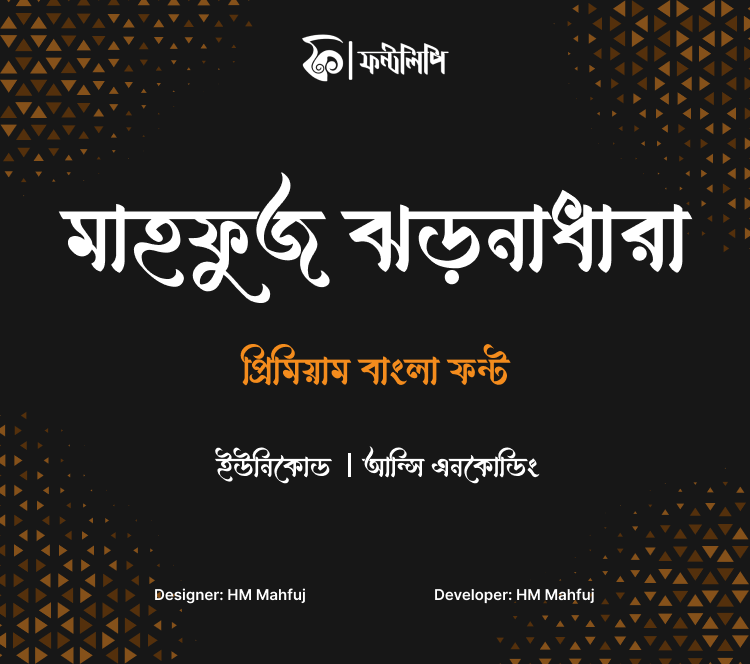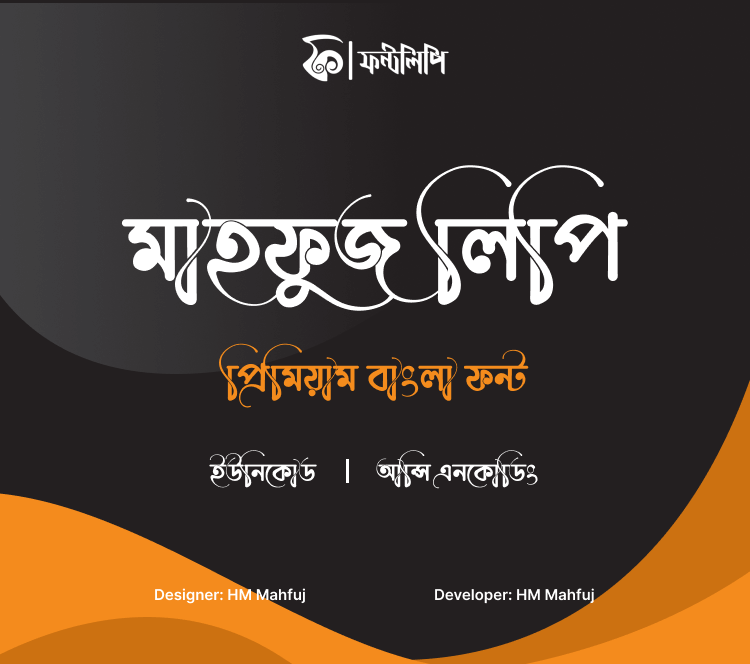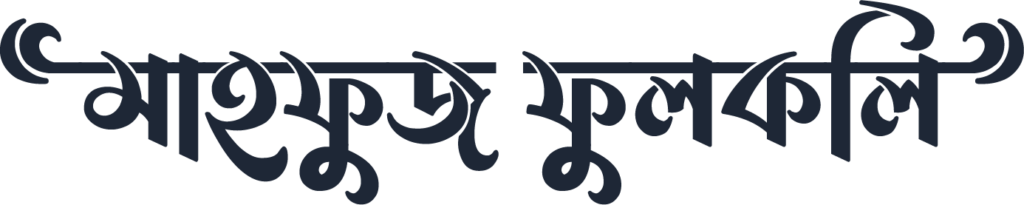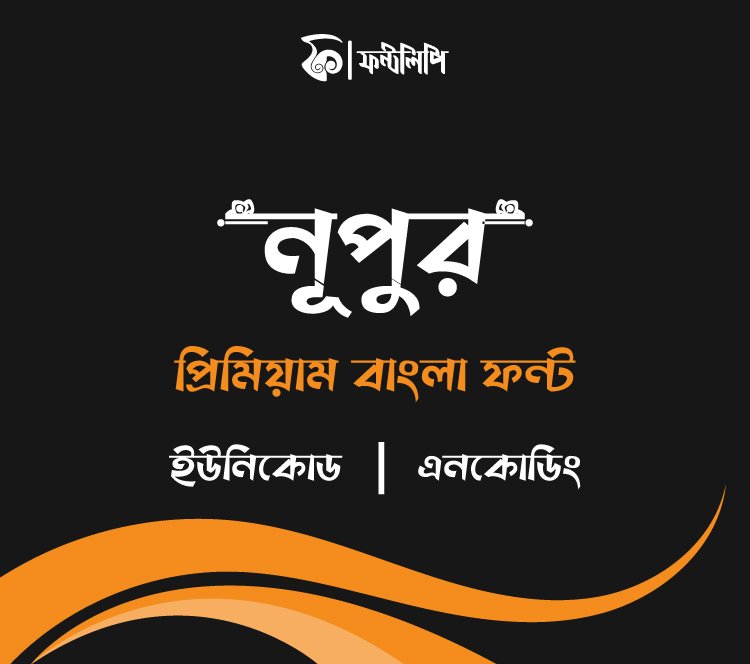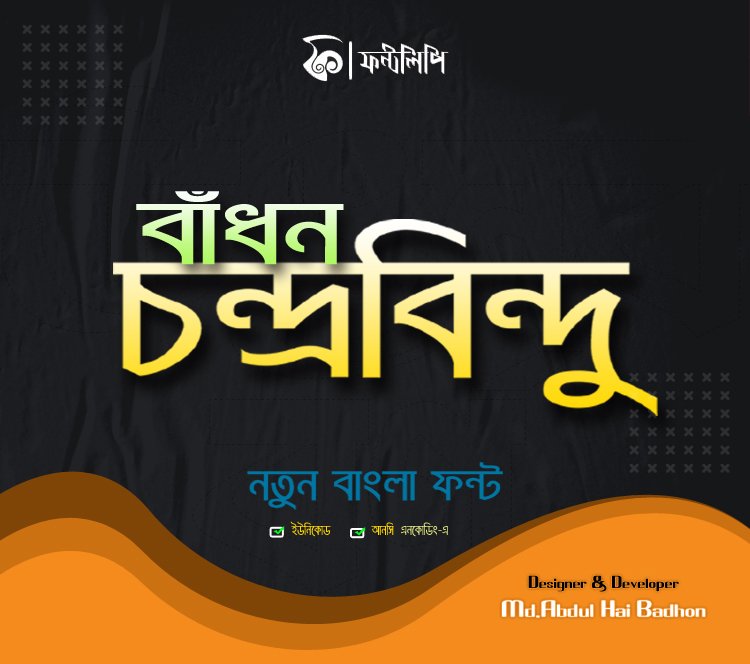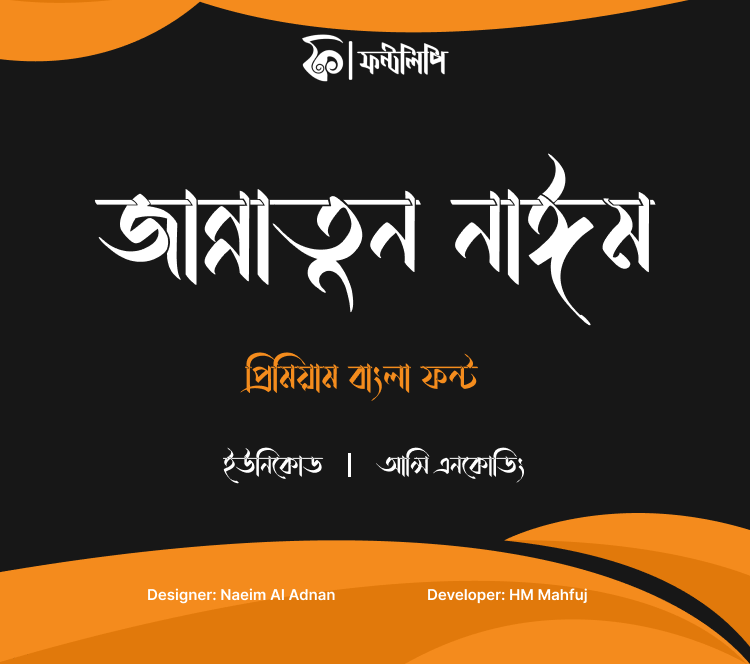
বাংলা পোস্টার ডিজাইনের জন্য সেরা ১০টি বাংলা ফন্ট: রিভিউ ও বিশ্লেষণ
বাংলা পোস্টার ডিজাইন এখন আগের চেয়ে আরও বেশি জনপ্রিয়। ডিজিটাল মার্কেটিং, সোশ্যাল মিডিয়া, অফিসিয়াল বিজ্ঞাপন, শিক্ষা প্রতিষ্ঠান—সবখানে পোস্টারের চাহিদা বাড়ছে। সুন্দর ও মানানসই ফন্ট ব্যবহার করলে পোস্টার সহজেই মানুষের দৃষ্টি আকর্ষণ করে, পোস্টারের গুরুত্ব বাড়ে, এবং বার্তা পরিষ্কারভাবে পৌঁছায়। ডিজাইনারদের জন্য ফন্ট নির্বাচন সবচেয়ে গুরুত্বপূর্ণ বিষয়গুলোর একটি। বাজারে অনেক বাংলা ফন্ট আছে, কিন্তু সবগুলোই পোস্টার ডিজাইনের জন্য উপযুক্ত নয়। কিছু ফন্ট খুব সুন্দর হলেও পড়তে কষ্ট হয়, আবার কিছু ফন্ট দেখতে ক্লাসিক হলেও আধুনিক পোস্টারে মানানসই হয় না।
আজ আমরা এমন ১০টি বাংলা ফন্ট নিয়ে আলোচনা করব, যেগুলো পোস্টার ডিজাইনের জন্য দারুণ উপযোগী। ফন্টগুলো সরাসরি ফন্টলিপি ডটকম থেকে সংগ্রহ করা হয়েছে এবং প্রতিটির জন্য সংক্ষিপ্ত রিভিউ, মূল বৈশিষ্ট্য ও ব্যবহারিক উপকারিতা তুলে ধরা হয়েছে। এই বিশ্লেষণ শুধু ডিজাইনারদের জন্য নয়, যারা নতুন পোস্টার তৈরি করতে চান বা ফন্ট নিয়ে এক্সপেরিমেন্ট করতে চান, তাদের জন্যও সহায়ক।
পোস্টারের জন্য সঠিক ফন্ট নির্বাচন করলে ডিজাইনের মান বাড়ে এবং দর্শক সহজেই আকৃষ্ট হয়। নিচে ১০টি সেরা বাংলা ফন্টের বিস্তারিত রিভিউ এবং বিশ্লেষণ দেয়া হলো।
১. আমিঃ মুসলিম ফন্ট
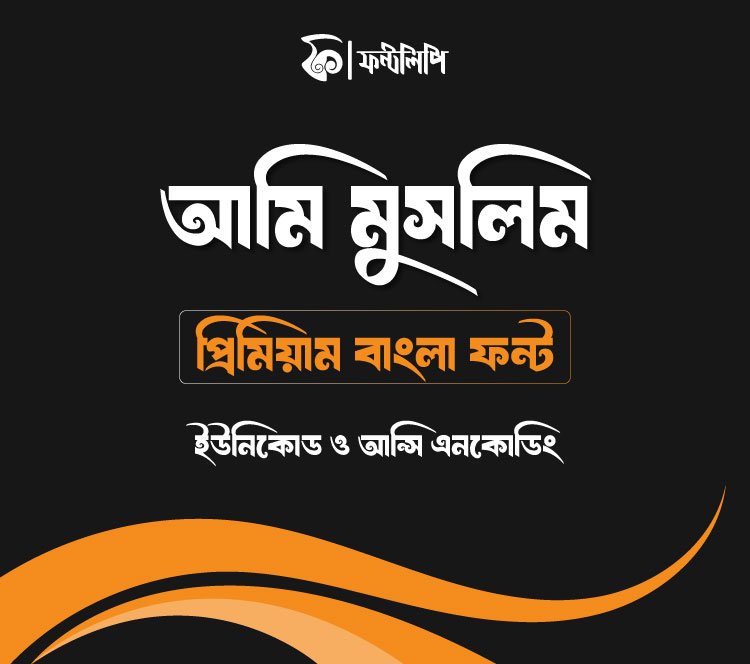
সংক্ষিপ্ত রিভিউ:
আমিঃ মুসলিম ফন্ট আধুনিক ও ইসলামিক ভাবধারার সংমিশ্রণ। এই ফন্টের অক্ষরগুলো দেখতে একটু ভারী, স্পষ্ট এবং বোল্ড, তাই ধর্মীয় পোস্টারে গুরুত্ব বাড়ে। যারা ধর্মীয় বা ইসলামিক অনুষ্ঠান, পোস্টার ও ব্যানারে বিশেষ চেহারা দিতে চান, তাদের জন্য এই ফন্টটি আদর্শ। ফন্টের স্টাইল দেখতে আকর্ষণীয় এবং লেখাগুলো সহজেই চোখে পড়ে। বিশেষ করে ইসলামিক কনটেন্টে ফন্টটি খুব মানানসই।
এটি শুধু ধর্মীয় নয়, অফিসিয়াল এবং ফরমাল পোস্টারেও ব্যবহার করা যায়। বেশ কিছু ডিজাইনার এই ফন্টকে ইসলামিক বইয়ের প্রচ্ছদ, মসজিদ-সংক্রান্ত বিজ্ঞাপন বা ওয়াজ মাহফিলের ব্যানারে ব্যবহার করেন। ফন্টের ভারী স্ট্রোক ও ঘনত্ব পোস্টারকে আরও দৃঢ় ও বিশ্বাসযোগ্য করে তোলে।
নতুন ডিজাইনাররা অনেক সময় ফন্টের স্টাইল নিয়ে দ্বিধায় পড়েন, তবে আমিঃ মুসলিম ফন্টের ইউনিক ইসলামিক ছোঁয়া এবং বোল্ডনেস কোন পোস্টারে সহজেই আলাদা করে তোলে। আরেকটি গুরুত্বপূর্ণ বিষয়, ফন্টটি ছোট ও বড়—দুই ধরনের সাইজে ভালো কাজ করে; ছোট পোস্টারেও অক্ষর স্পষ্ট থাকে, বড় ব্যানারেও ফন্টের সৌন্দর্য বজায় থাকে।
এই ফন্টের অক্ষর ক্যালিগ্রাফি স্টাইলের হলেও পড়তে সহজ। ইসলামিক ইভেন্টে ব্যবহার করলে দর্শকের কাছে বার্তা দ্রুত পৌঁছে যায়।
মূল বৈশিষ্ট্য:
- ইউনিকোড সাপোর্টেড, তাই সব প্ল্যাটফর্মে চলে
- ঘন ও স্পষ্ট অক্ষর—ফন্টের ওজন বেশি, চোখে পড়ে
- ইসলামিক ছোঁয়া—স্টাইল ও কার্ভে ধর্মীয় আবহ
- বড় আকারে স্পষ্টতা বজায় রাখে—ব্যানার, ফ্লেক্সে বিকৃত হয় না
ব্যবহারিক উপকারিতা:
ইসলামিক উৎসব, মসজিদ, মাদ্রাসা, ধর্মীয় অনুষ্ঠান কিংবা ইসলামিক বইয়ের কভার ডিজাইন—এ ধরনের কাজে এই ফন্টটি দুর্দান্ত। কারণ, ফন্টের প্রতিটি অক্ষরে ধর্মীয় ভাব ফুটে ওঠে। ছোট-বড় যে কোনো সাইজের পোস্টারেও ফন্টটি পরিষ্কার ও পাঠযোগ্য থাকে।
নতুনদের জন্য একটি টিপস: ধর্মীয় পোস্টারে সাধারণত আকর্ষণীয় ও স্পষ্ট ফন্ট ব্যবহার করা হয়, যাতে দর্শক সহজেই বার্তা বুঝতে পারে। আমিঃ মুসলিম ফন্ট ব্যবহার করলে পোস্টারের পেশাদারিত্ব বাড়ে। আরেকটি গুরুত্বপূর্ণ বিষয়—অনেক ইসলামিক ফন্ট শুধু বড় আকারের জন্য উপযোগী, কিন্তু আমিঃ মুসলিম ফন্ট ছোট পোস্টার, সোশ্যাল মিডিয়া পোস্ট বা ফ্লায়ারেও ভালো কাজ করে।
২. হুমায়রা লিপি
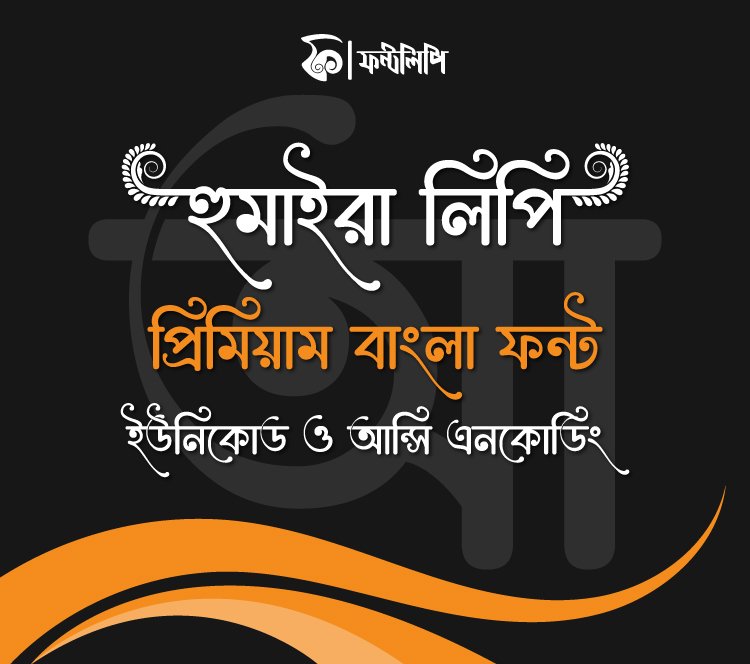
সংক্ষিপ্ত রিভিউ:
হুমায়রা লিপি ক্লিন ও স্মার্ট লুকের একটি ফন্ট। যারা আধুনিক এবং সহজ পাঠযোগ্য ফন্ট খুঁজছেন, তাদের জন্য এটি ভালো পছন্দ। বেশিরভাগ ডিজাইনার সামাজিক প্রচারণা বা সাধারণ বিজ্ঞাপনের পোস্টারে এই ফন্ট ব্যবহার করতে স্বাচ্ছন্দ্যবোধ করেন।
ফন্টের অক্ষরগুলো সরল, পাতলা এবং খুবই স্পষ্ট। ডিজাইন সিম্পল এবং মিনিমালিস্টিক। বিশেষ করে বিজ্ঞাপন পোস্টার, স্কুল-কলেজের নোটিশ, কিংবা ছোট ব্যানারে এই ফন্ট খুব সহজে পড়া যায়। যারা পেশাদার ডিজাইন করতে চান, তাদের জন্য এটি আদর্শ।
একটি বড় সুবিধা—ফন্টটি সকল ব্রাউজারে সমানভাবে কাজ করে, অর্থাৎ মোবাইল, ল্যাপটপ, ডেস্কটপ—সবখানে একইভাবে দেখা যায়। হুমায়রা লিপি ফন্টের স্টাইলিশ কাটিং পোস্টারকে আধুনিক করে তোলে, এবং ডিজাইন সহজ, স্লিক ও প্রফেশনাল দেখায়।
নতুন ডিজাইনাররা অনেক সময় ফন্টের জটিলতা নিয়ে চিন্তা করেন, কিন্তু হুমায়রা লিপি ফন্টে সেই সমস্যা নেই। সরল, পরিষ্কার এবং পেশাদার লুক পাওয়া যায়।
মূল বৈশিষ্ট্য:
- স্পষ্ট ও সহজ অক্ষর—ডিজাইন মিনিমাল, পড়তে সহজ
- ইউনিকোড সাপোর্ট—সব প্ল্যাটফর্মে চলে
- স্টাইলিশ কাটিং—অক্ষরের কাটিং স্মার্ট
- সকল ব্রাউজারে সমানভাবে কাজ করে—কোনো সমস্যা হয় না
ব্যবহারিক উপকারিতা:
প্রাত্যহিক বিজ্ঞাপন, ব্যানার, নোটিশ কিংবা স্কুল-কলেজের ইভেন্ট পোস্টারে এই ফন্টটি ব্যবহার উপযোগী। ফন্টের সরলতা ও স্মার্টনেস পোস্টারকে পেশাদার করে তোলে। সাধারণ মানুষ খুব সহজেই পড়তে পারে, তাই ম্যাস মার্কেটিংয়ের জন্য আদর্শ।
নতুনদের জন্য পরামর্শ: যারা সামাজিক মিডিয়ার জন্য পোস্টার তৈরি করেন, তাদের জন্য হুমায়রা লিপি ফন্ট একটি পারফেক্ট চয়েস। কারণ, সোশ্যাল মিডিয়ার পোস্টে ফন্ট পরিষ্কার ও সহজ হওয়া জরুরি, যাতে দর্শক দ্রুত পড়তে পারে।
আরেকটি ছোট টিপ—এই ফন্টটি এডুকেশনাল ও ফরমাল পোস্টারে ব্যবহার করলে বার্তা আরও স্পষ্টভাবে পৌঁছায়।
৩. হযরত আবু হুরায়রা ফন্ট
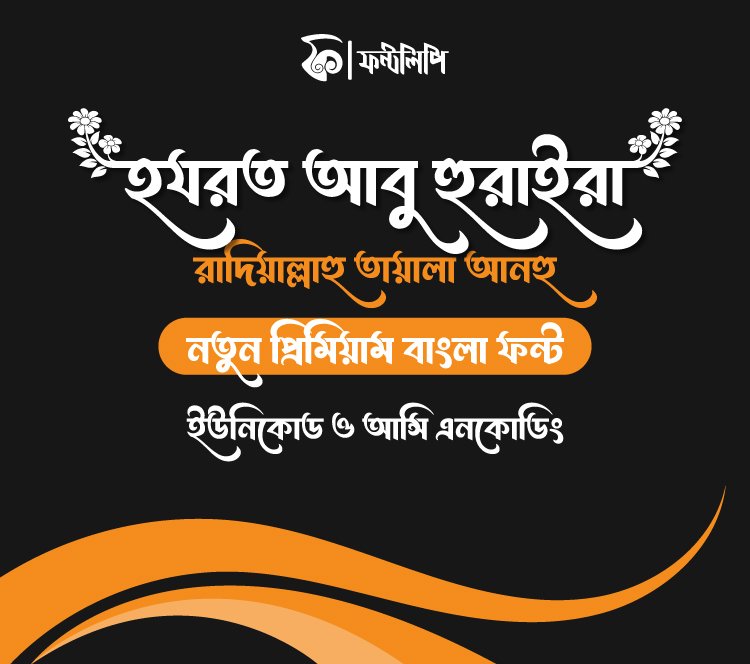
সংক্ষিপ্ত রিভিউ:
হযরত আবু হুরায়রা ফন্ট দেখলেই বোঝা যায়, এটি ইসলামিক পোস্টার বা ব্যানারের জন্য বিশেষভাবে তৈরি। ফন্টের অক্ষরগুলো একটু ঘন এবং শক্তিশালী। ফলে ধর্মীয় কনটেন্টে লেখা গুলো আরও গুরুত্ব পায়।
এটি মূলত ধর্মীয় অনুষ্ঠান, মাহফিল, সেমিনার, কিংবা ওয়াজের পোস্টারে ব্যবহারের জন্য উপযুক্ত। ফন্টের বোল্ড স্ট্রোক এবং ভারী কাটিং পোস্টারে গুরুত্ব দেয়। ডিজাইনাররা এ ধরনের ফন্টের মাধ্যমে দর্শকের চোখে গুরুত্ব বাড়াতে চান, কারণ ধর্মীয় বার্তা স্পষ্ট ও শক্তিশালী হওয়া দরকার।
অভিজ্ঞ ডিজাইনারদের মতে, পোস্টারের জন্য ফন্ট শুধু স্টাইল নয়, বার্তা পৌঁছানোর শক্তি। ফন্টের সৌন্দর্য, পাঠযোগ্যতা এবং স্পষ্টতা—সবকিছু মিলিয়ে পোস্টার ডিজাইন সফল হয়।